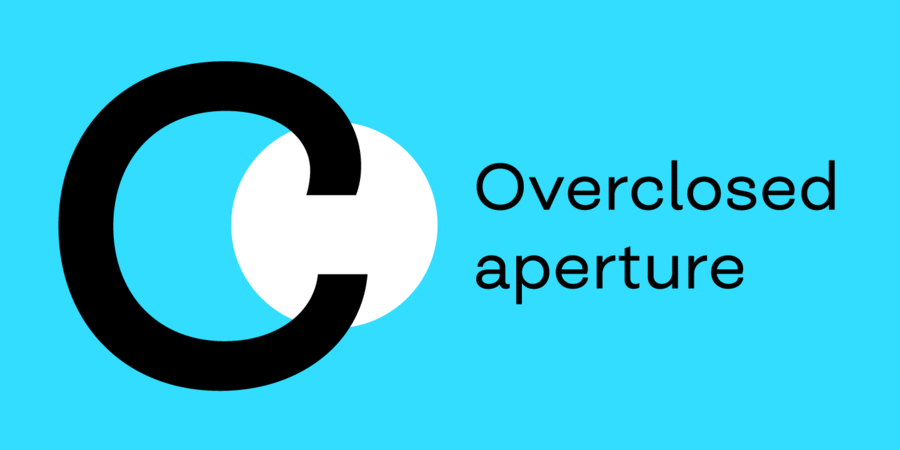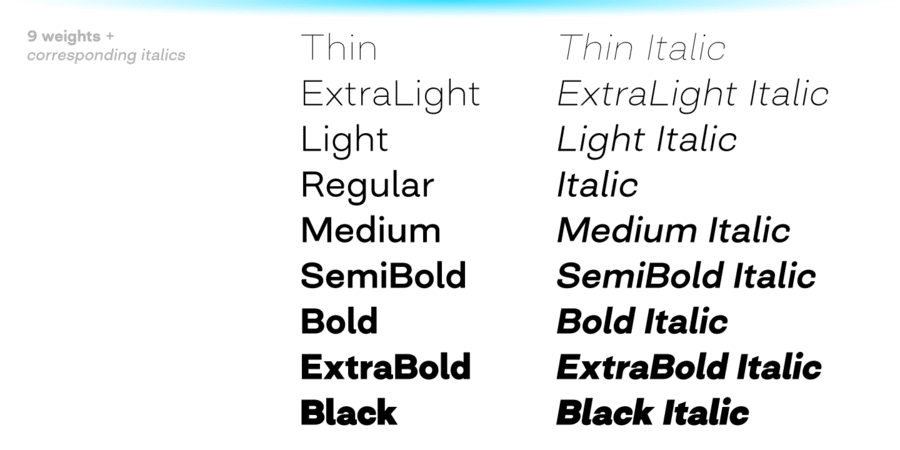
Closer – це шрифт з високим ступенем адаптованості до вимог користувачів. Його можна охарактеризувати як швейцарський гротеск з закритою апертурою. З огляду на те, що Closer трохи ширше звичайних гротесків і має гуманістичні форми, він виглядає менш прісним, але все ще відносно нейтральним.
Closer складається з 9 накреслень (в цілому 18 стилів), має розширену підтримку мов, включно з кирилицею, і володіє широкими можливостями з 7 стилістичними наборами для змішування і знаходження найкращих поєднань.
Шрифт розробив Андрій Константинов у 2019 році.
Особливості сімейства шрифтів CloserХіт десятиліття:
Асоціації з сімейством шрифтів CloserОсобистість і характер гарнітури:
лаконічний, міський, якісний, сучасний, модний, холодний, тонкий, легкий, ясний, чистий, невагомий, прозорий, гладенький, крихкий, дротяний, гнучкий, оригінальний, добрий, приємний, делікатний, прохолодний, культурний, багатий, ніжний, затишний, неоновий, інтимний, сексуальний, комфортний, скляний, свіжий, стабільний, статичний, стійкий, глобалізований, глобалістічний, технічний, впевнений, надійний, спортивний, важливий, переконливий, наполегливий, строковий, потужний, сильний, авторитетний, помітний, важкий, індустріальний, крутий
дизайн, чистота, гігієна, шампунь, дієта, краса, туалетна вода, косметика, мода, АСМР, парфумерія, лосьйон, Місто, здоров'я, екологія, одяг, йога, вода, ліки, торгівля, Локдаун, захист, тренажери, верстат, машинобудування, промисловість, енергетика, електростанція, вантажоперевезення, вантажівка, спорт, інструмент, мотор, двигун, шоу, телебачення, металургія, Доставка Гарнітура має ознаки стилів: